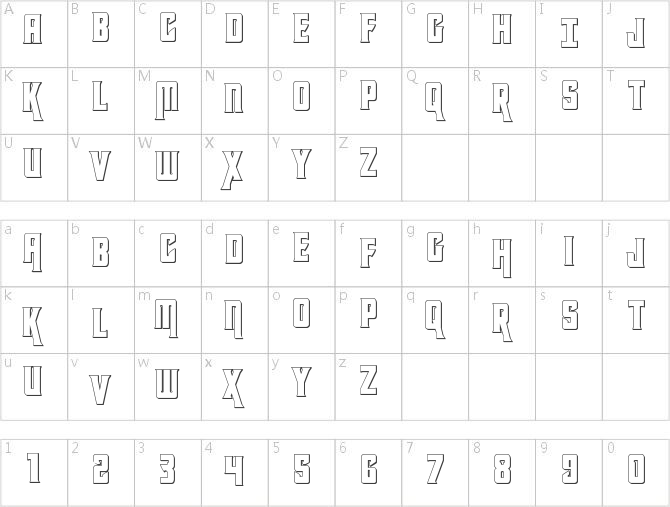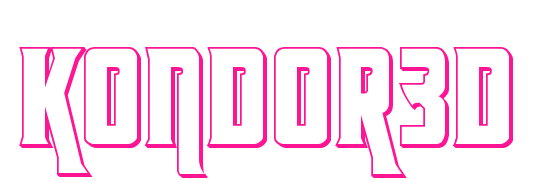
字體名稱(chēng): kondor3
kondor3d介紹
kondor3d字體字庫(kù)是一款讓人賞心悅目、百看不厭的英文字體,適合各類(lèi)廣告和產(chǎn)品包裝設(shè)計(jì)應(yīng)用,字體大小0.07MB,格式為ttf字體,上傳用戶(hù)是sunlight,作者/版權(quán)方為未知